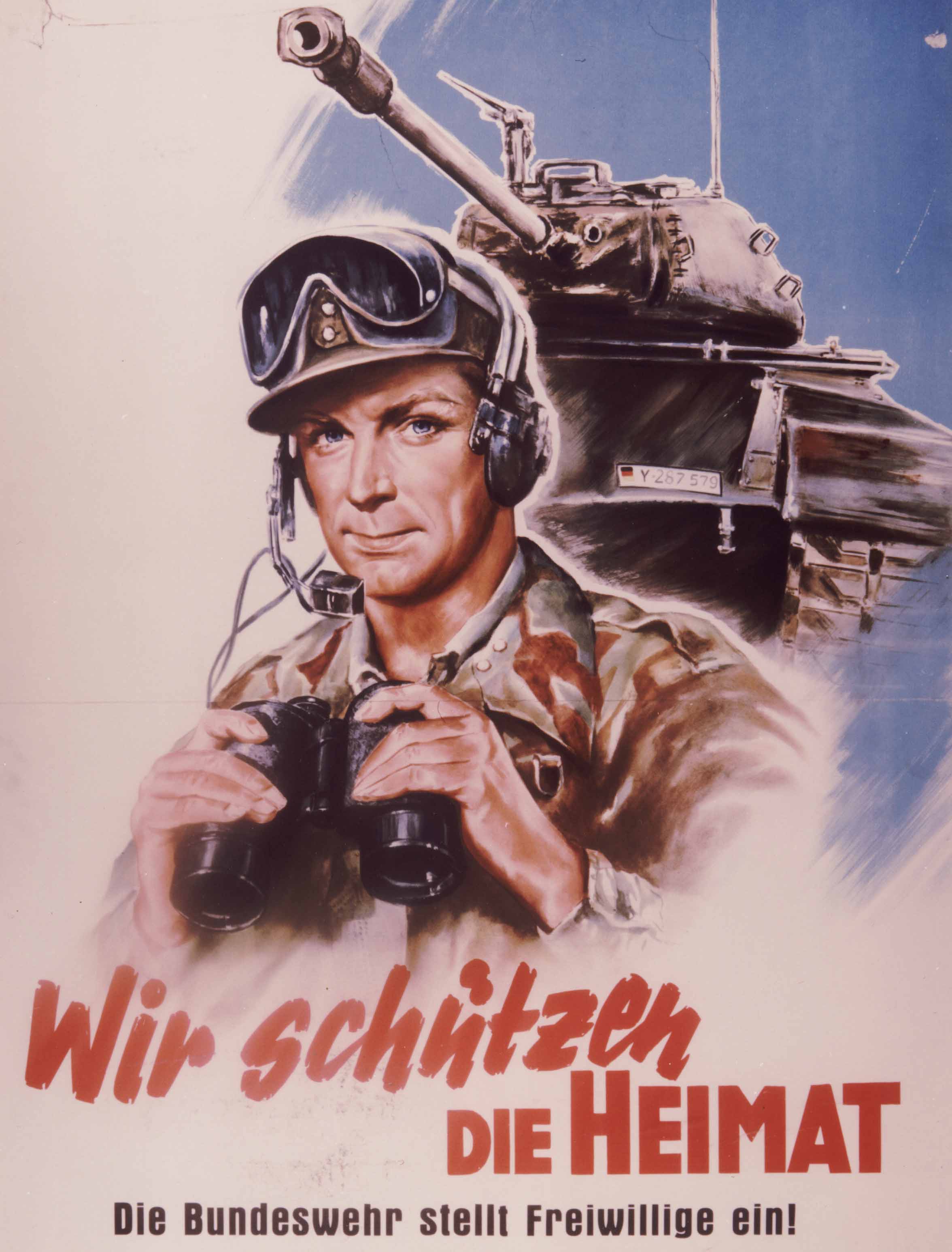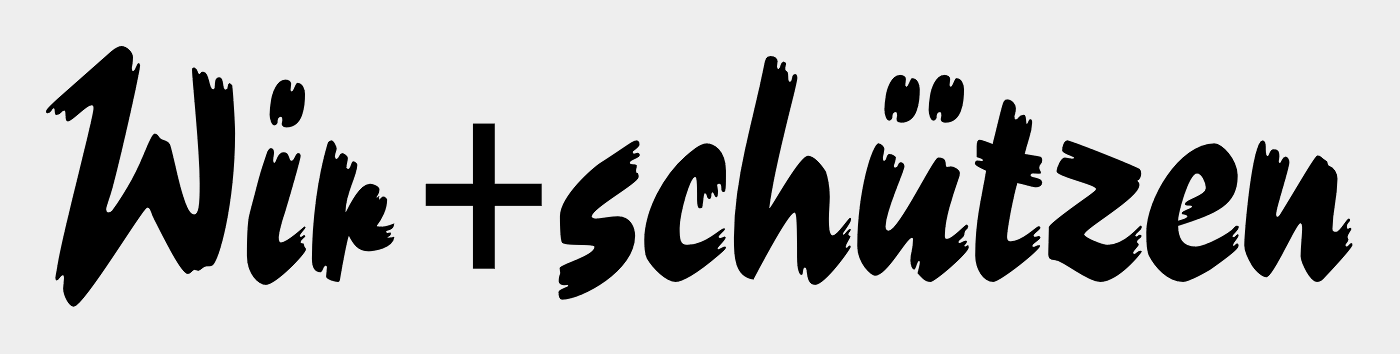
Suche Schriftart
Ich suche für meinen Vater eine bestimmte Schriftart, die früher häufig für DDR-Propaganda benutzt wurde. Er ist Modelleisenbahner und würde gerne verschiedene Ausdrucke für seine Modelle anfertigen.
Vielleicht erkennt es ja jemand (siehe Bild. Um das "Wir schützen" gehts ^^) und kann mir sagen ob es das auch als herunterladbare Schriftart gibt.
Polo hat auch einige Ähnlichkeiten, aber wenn ich mir die stürzende en-Ligatur so ansehe, vermute ich fast, daß das handgeschrieben ist.
Das Beispiel entspringt der Bundeswehr von 1960, keinen DDR-Truppen. Der Panzer ist ein M-47, den hatte die Bundeswehr von den Amis geerbt. War auch leichter, als die Dinger wieder über den Teich zu schaffen.
… und hier ein hochaufgelöstes Bild davon: